싸인은 단순한 서명이 아니라 자신을 표현하는 디자인 요소예요. 특히 감각적인 싸인은 더 세련되고 독창적인 인상을 남길 수 있답니다! ✨ 오늘은 싸인을 더욱 멋지게 보이게 하는 3가지 디자인 요소를 알아볼게요. 🚀
감각적인 싸인이 중요한 이유 🤔
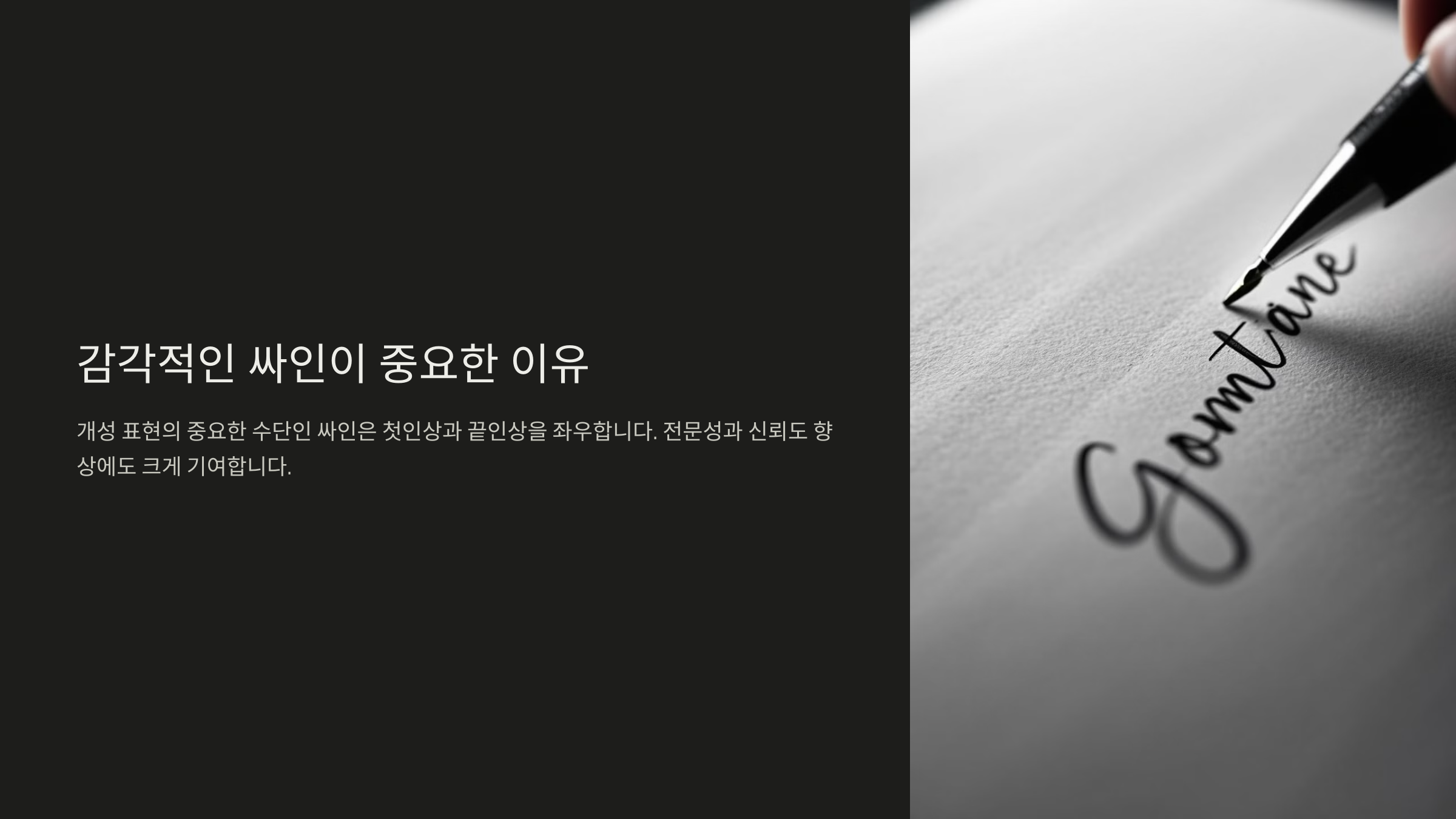
싸인의 스타일은 첫인상과 신뢰도에 영향을 줄 수 있어요. 그렇다면 감각적인 싸인은 왜 중요할까요?
📌 감각적인 싸인의 장점
이점 설명 더 세련된 느낌 균형 잡힌 디자인은 더욱 깔끔하고 고급스러워 보여요. 개성 표현 독창적인 스타일을 반영하면 차별화된 싸인을 만들 수 있어요. 신뢰도 상승 정돈된 싸인은 더 신뢰감 있고 전문적인 인상을 줍니다. 이제 감각적인 싸인의 중요성을 알았으니, 첫 번째 디자인 요소인 '자연스러운 흐름'에 대해 알아볼까요? 😊
1. 자연스러운 흐름 🔄
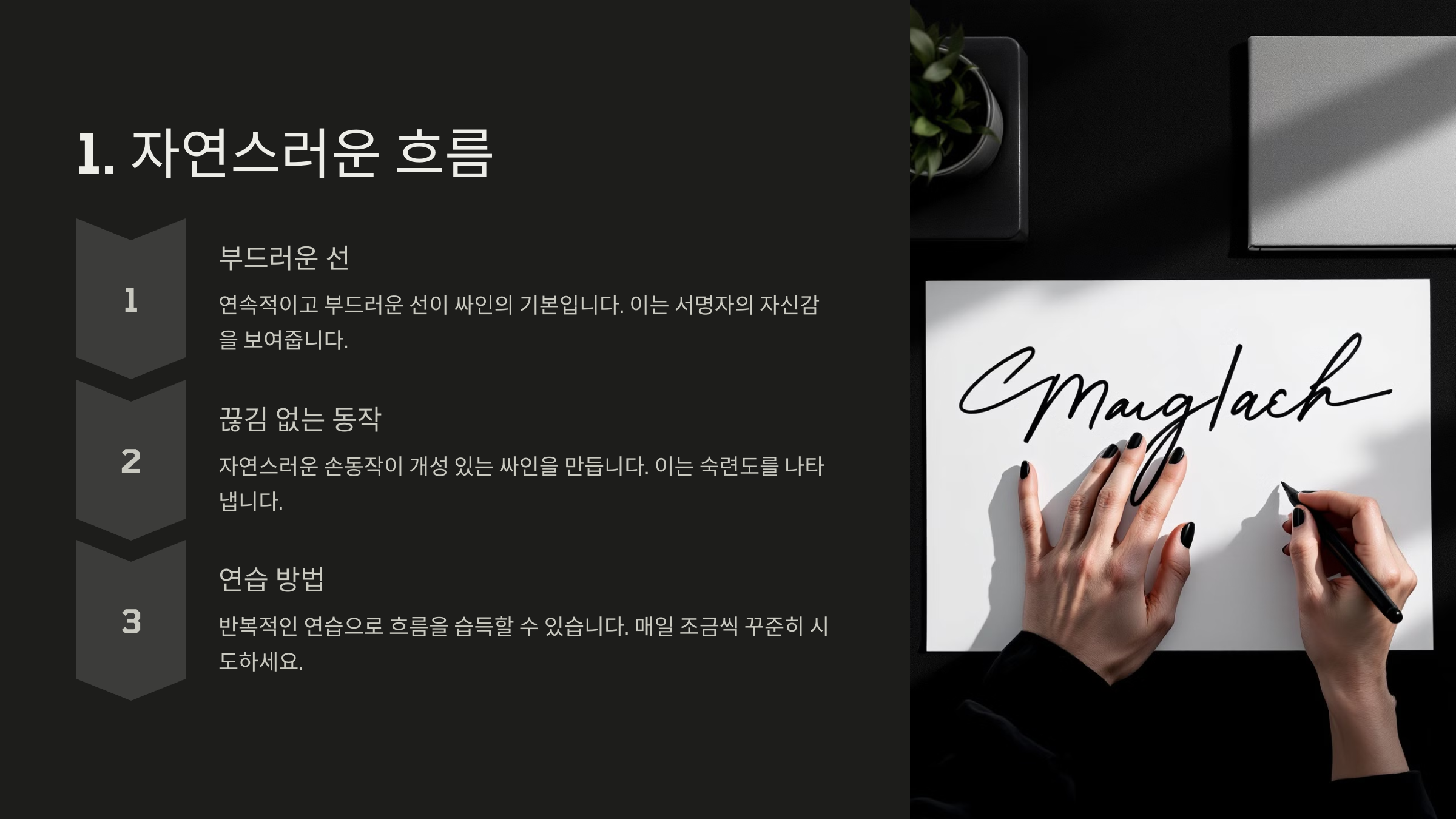
감각적인 싸인을 만들려면 글자의 흐름이 부드럽고 자연스러워야 해요. 싸인이 끊기지 않고 유려하게 연결되면 더욱 세련된 인상을 줄 수 있답니다! ✍
📌 자연스러운 흐름을 만드는 3가지 방법
- ✔ 획을 부드럽게 연결 → 글자가 부드럽게 이어지면 더 세련돼 보여요.
- ✔ 곡선을 활용 → 직선만 쓰는 것보다 곡선을 섞으면 싸인이 더 자연스러워요.
- ✔ 이니셜과 마지막 글자 강조 → 시작과 끝 부분을 조절하면 더욱 멋진 싸인이 돼요.
이제 자연스러운 흐름을 익혔다면, 두 번째 요소인 '강약 조절'을 통해 싸인을 더 감각적으로 만들어볼까요? 😆
2. 강약 조절 🎭
싸인을 더욱 감각적으로 만들려면 획의 강약을 조절하는 것이 중요해요. 획이 일정한 두께로만 이루어지면 밋밋할 수 있어요! 강한 획과 약한 획을 조합하면 더 다이나믹한 싸인을 만들 수 있답니다. 💡
📌 강약 조절하는 3가지 방법
기법 효과 굵은 시작, 가는 마무리 강렬한 인상을 주면서도 부드러운 마무리를 연출할 수 있어요. 이니셜 강조 첫 글자를 더 강하게 하면 시각적 포인트를 줄 수 있어요. 획의 길이 조절 일정한 길이 대신 변화를 주면 더 스타일리시한 싸인이 돼요. 이제 강약 조절까지 배웠어요! 그럼 마지막으로 세 번째 요소인 '균형 잡힌 구성'을 알아볼까요? 😊
3. 균형 잡힌 구성 ⚖
감각적인 싸인은 균형이 잘 맞아야 세련되게 보일 수 있어요. 글자 크기, 간격, 정렬을 조절하면 더욱 조화로운 싸인을 완성할 수 있답니다. 🎨
📌 균형 잡힌 싸인을 위한 3가지 원칙
원칙 설명 이니셜과 본문 크기 조절 이니셜은 크고 강하게, 나머지 글자는 가볍게 쓰면 더 세련돼 보여요. 균일한 간격 유지 글자 사이의 간격이 일정해야 안정적인 디자인이 돼요. 마무리 강조 싸인의 끝을 정리해서 마무리하면 더 완성도 높은 느낌을 줄 수 있어요. 이제 균형 잡힌 싸인을 만드는 법까지 마스터했어요! 그럼 실제로 유명인의 감각적인 싸인을 살펴보면서 더 많은 아이디어를 얻어볼까요? 🤩
유명인의 감각적인 싸인 사례 🌟
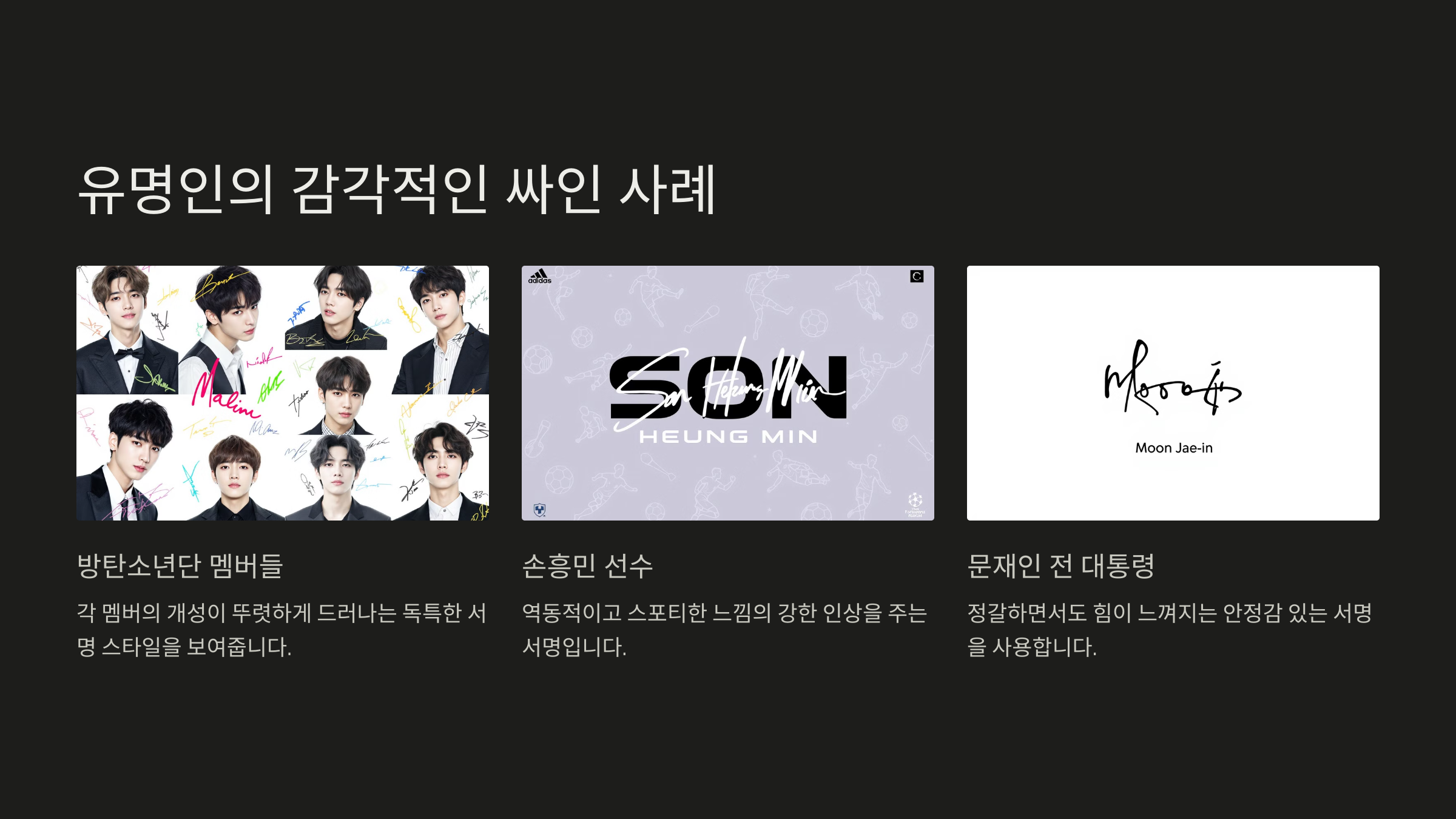
많은 유명인들은 싸인을 통해 자신만의 개성을 표현하고 있어요. 그들의 싸인을 분석하면 더 감각적인 싸인을 디자인하는 법을 배울 수 있답니다! ✍
📌 유명인의 감각적인 싸인 스타일 비교
유명인 싸인 스타일 특징 스티브 잡스 심플하고 미니멀한 스타일 곡선을 배제하고 직선으로 균형을 맞춤 일론 머스크 강한 직선과 기울기 직선적인 서명으로 강한 인상을 줌 마이클 조던 곡선형 필기체 자연스러운 흐름을 강조해 감각적인 느낌 연출 지드래곤 (G-Dragon) 이니셜 + 기호 활용 독창적인 디자인으로 개성을 표현 이처럼 작은 변화만으로도 싸인의 분위기가 완전히 달라질 수 있어요! 그럼 마지막으로 더 감각적인 싸인을 만들기 위한 추가 팁을 알려드릴게요. 😊
멋진 싸인을 위한 추가 팁 ✨
지금까지 배운 요소들을 활용하면 감각적인 싸인을 만들 수 있어요. 하지만! 조금 더 디테일을 살리면 더욱 완성도 높은 싸인을 만들 수 있답니다. 😊
📌 감각적인 싸인을 위한 3가지 추가 팁
- ✔ 이니셜을 독창적으로 변형하기 → 첫 글자 디자인을 과감하게 바꿔보세요.
- ✔ 싸인의 마지막 획을 길게 빼기 → 마무리를 강조하면 더 인상적인 싸인이 돼요.
- ✔ 작은 기호 추가 → 점(•), 별(⭐), 밑줄(━) 등을 활용해 개성을 살릴 수 있어요.
이제 싸인의 기본 원칙과 추가 팁까지 모두 배웠어요! 마지막으로 싸인 디자인과 관련된 FAQ를 확인하면서 궁금증을 해결해볼까요? 🤩
FAQ ❓
Q1. 싸인을 감각적으로 보이게 하는 가장 쉬운 방법은?
A1. 가장 쉬운 방법은 이니셜을 강조하고, 글자의 흐름을 부드럽게 만드는 것! 이니셜을 독창적으로 변형하고 획의 강약을 조절하면 더욱 멋진 싸인이 돼요. ✍
Q2. 싸인의 흐름을 자연스럽게 만들려면 어떻게 해야 하나요?
A2. 글자 간 연결이 끊기지 않도록 곡선을 활용하는 것이 중요해요! 또한 획의 흐름을 일정하게 유지하면 더 세련된 느낌을 줄 수 있어요. 😊
Q3. 싸인에서 글자 크기를 조절하는 팁이 있을까요?
A3. 네! 이니셜을 더 크고 굵게 쓰고, 나머지 글자는 가볍게 조절하세요. 이렇게 하면 자연스럽게 균형 잡힌 싸인이 완성된답니다. 🎨
Q4. 싸인을 만들 때 피해야 할 실수는?
A4. ❌ 너무 복잡한 디자인 → 싸인이 알아보기 어렵고 가독성이 떨어져요. ❌ 불균형한 글자 크기 → 한쪽이 너무 크거나 작으면 조화롭지 않아요. ❌ 획이 일정하지 않음 → 강약 조절이 없는 싸인은 단조로워 보일 수 있어요. 😉
Q5. 싸인을 더 독창적으로 만들기 위한 비결이 있을까요?
A5. 자신만의 개성을 담는 것이 중요해요! ✔ 독창적인 이니셜 변형 ✔ 기호(⭐, __, •) 활용 ✔ 강약 조절을 통해 스타일 추가 이렇게 하면 더 특별한 싸인을 만들 수 있어요. 😆
감각적인 싸인은 조금만 신경 쓰면 더욱 세련된 스타일을 완성할 수 있어요! ✔ 자연스러운 흐름 만들기 ✔ 획의 강약 조절 ✔ 균형 잡힌 구성 유지 이 세 가지를 기억하면서 더 감각적인 싸인을 연습해 보세요! 🚀